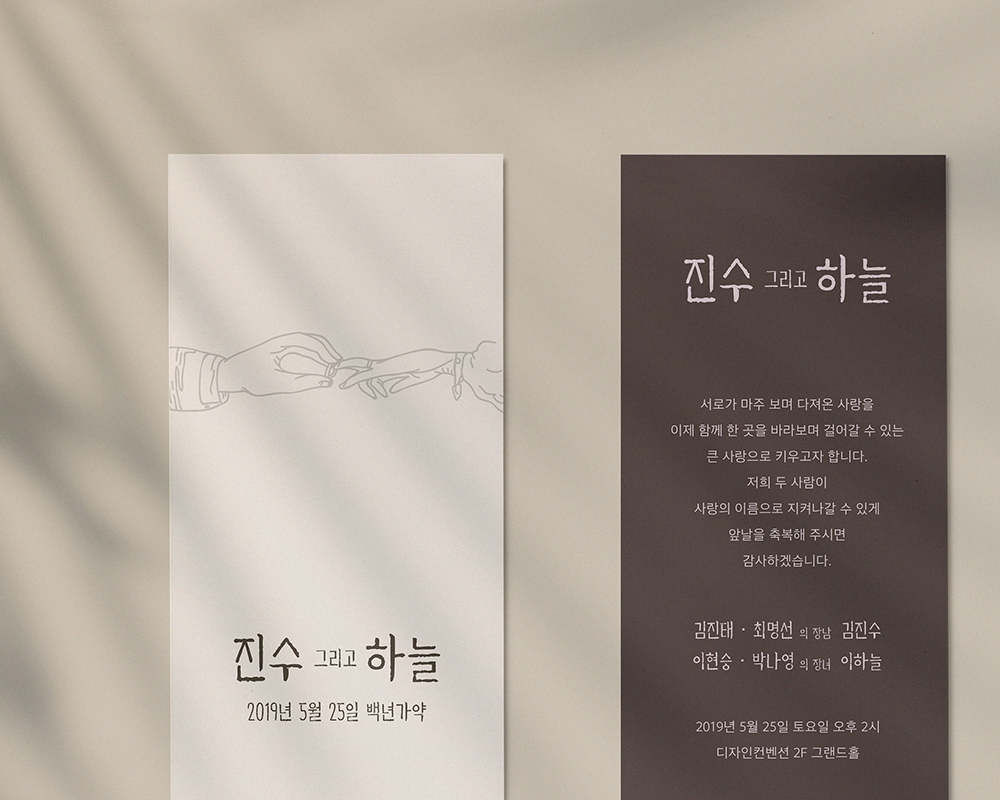
뿌리깊은 프로젝트의 일환으로 (주)디자인210에서 시대별 의미있는 글씨를 연구하며 뜻을 이어가고자 석보상절을 시작으로 앞으로 출시되는 뿌리깊은 서체들이 3년간 개발, 런칭, 배포된다고 합니다. 그 세번째 폰트인 목우자수심결은 다음과 같은 내용을 담고 있습니다.
목우자수심결은 1400년대의 초기 한글 특징을 고스란히 가진 글꼴로, 글꼴이 가진 성격을 현대적으로 재해석해 디자인하였다. 판목(版木)으로 찍어낸듯한 거친 질감은 옛 글꼴의 디테일을 살려주며, 획의 기울기가 없는 수평, 수직의 형태와, 긴 장방형의 자형으로 다양한 굵기의 필획이 큰 특징이다. 전체적인 자형은 판본체 형태를 유지하지만, 기필과 수필의 필획으로 필사체의 모습을 또렷하게 표현하였다.